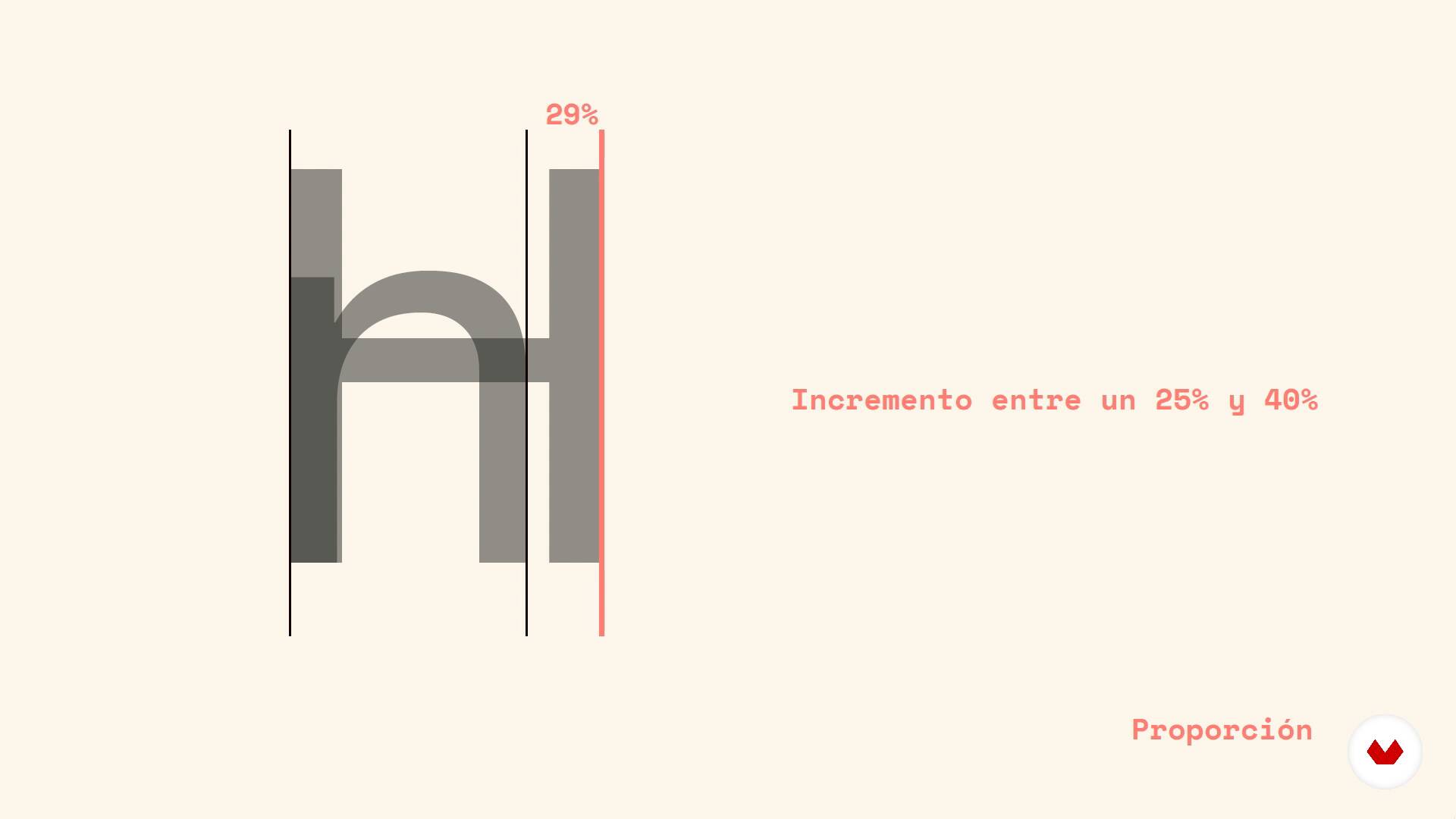
Digitale Neuinterpretation klassischer Schriftarten
High-Box-Systematisierung I.
Über die Videolektion: High-Box-Systematisierung I.
“Sobald die erste Version der Kleinbuchstaben entwickelt wurde, ist es Zeit, die Großbuchstaben zu zeichnen. Sie haben eine viel strukturiertere Form und in dieser Lektion werden wir mehr über sie erfahren. ”
In dieser Videolektion behandelt Oscar Guerrero Cañizares das Thema: High-Box-Systematisierung I., das Teil dieses Domestika-Onlinekurses ist: Digitale Neuinterpretation klassischer Schriftarten. Lernen Sie die Methode der typografischen Wiederbelebung kennen, um alten Schriftarten ein neues digitales Leben zu verleihen.
Partielle Transkription des Videos
“Wir haben bereits gesehen, wie Zeichnen und Kleinbuchstaben funktionieren. Es ist Zeit, mit Großbuchstaben zu arbeiten. Diese beiden Kisten, wie wir bereits gesehen haben, Sie erschienen in zwei verschiedenen historischen Perioden. Sehen wir uns diese Besonderheiten der großen Box an. In dieser Lektion werden wir versuchen zu verstehen, wie wir die Formen anpassen werden die wir in Kleinbuchstaben für den Aufbau der Hochbox generieren. Es ist eine ziemlich große Herausforderung, denn als wir Proportionen sahen, in der Geschichte des Schreibens, Großbuchstaben waren vor Kleinbuchstaben, und ...”
Zusammenfassung des Kurses: Digitale Neuinterpretation klassischer Schriftarten